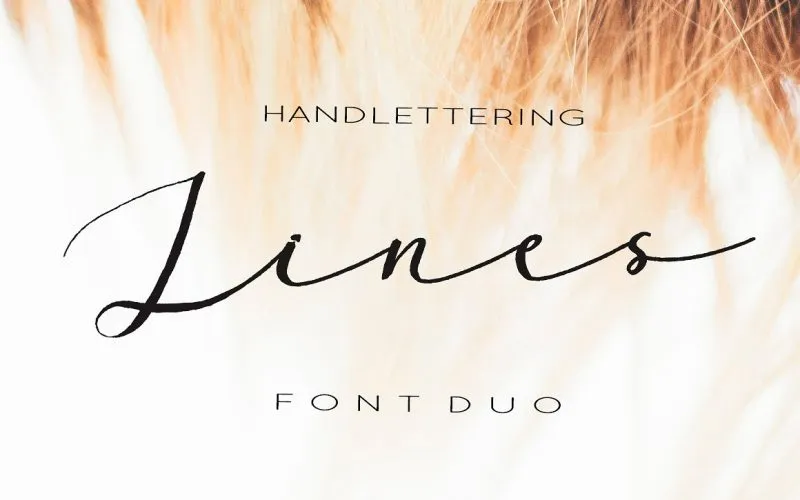
A Lines Font Duo é uma fonte script feminina e sensual, ideal para qualquer projeto visual que exija estilo elegante e leitura fácil. Ela se destaca pela sua simplicidade e alta legibilidade, tornando-a perfeita para diversos fins de uso. Esta fonte oferece múltiplas ligaturas, alternativas e suporte internacional para várias línguas da Europa Ocidental, incluindo inglês, francês, alemão e português. Seja você designer, escritor ou profissional de marketing, Lines Font Duo é uma escolha perfeita para criar layouts criativos que expressam elegância sem sacrificar o legibilidade. Seja em um logotipo sofisticado ou em uma invitativa de casamento requintada, na identidade visual de sua marca ou em qualquer tipo de material promocional – essa fonte tem a capacidade de deixar seu trabalho se destacando. Além disso, ela é ótima para cartazes, merchandising, cartas de felicitações, impressões de blog, roupas e até mesmo frases pessoais. Com Lines Font Duo, você está equipado com uma ferramenta versátil que pode transformar qualquer projeto em um desafio criativo e impecável. A escolha certa da fonte pode fazer toda a diferença entre um trabalho profissional e um design memorável.